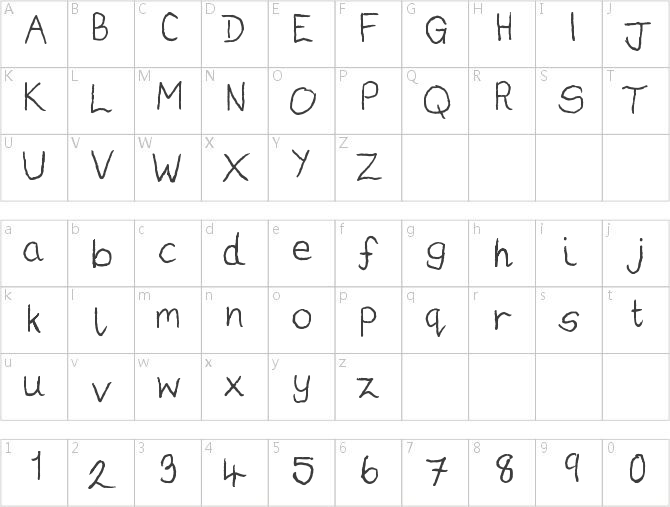
字体名称: Darius
Darius Gardner_'s Handwriting Re
Darius Gardner_'s Handwriting Re字体字库是一款让人赏心悦目、百看不厌的英文字体,适合各类广告和产品包装设计应用,字体大小0.06MB,格式为ttf字体,上传用户是翰池书法,作者/版权方为未知